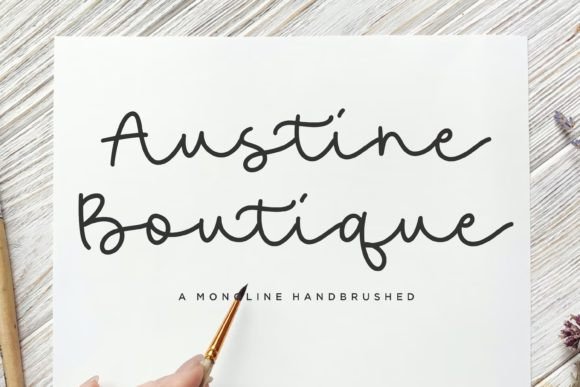
Austine Boutique
์˜ฌ๋ฐ”๋ฅธ ๋””์ž์ธ ์š”์†Œ๋ฅผ ์ฐพ๋Š” ๊ฒƒ์€ ์–ด๋ ค์šธ ์ˆ˜ ์žˆ์ง€๋งŒ Austine Boutique๋Š” ์ž‘์—…์„ ์ฆ‰์‹œ ํ–ฅ์ƒ์‹œํ‚ค๋Š” ๋›ฐ์–ด๋‚œ ์ปฌ๋ ‰์…˜์„ ์ œ๊ณตํ•ฉ๋‹ˆ๋‹ค.
์ •๋ฐ€ํ•˜๊ฒŒ ์ œ์ž‘๋œ Austine Boutique๋Š” ๊น”๋”ํ•œ ๋ฒกํ„ฐ, ๋ถ€๋“œ๋Ÿฌ์šด ํƒ€์ดํฌ๊ทธ๋ž˜ํ”ผ ๋ฐ ์•ˆ์‹ฌํ•  ์ˆ˜ ์žˆ๋Š” ์ƒ์—…์šฉ ๋ผ์ด์„ ์Šค๋ฅผ ์ œ๊ณตํ•ฉ๋‹ˆ๋‹ค.
POD(์ฃผ๋ฌธํ˜• ์ธ์‡„) ์ œํ’ˆ, ๊ฒฐํ˜ผ์‹ ์ดˆ๋Œ€์žฅ ๋˜๋Š” ์†Œ์…œ ๋ฏธ๋””์–ด ๊ทธ๋ž˜ํ”ฝ์„ ๋งŒ๋“ค ๋•Œ Austine Boutique๋Š” ์ด์ƒ์ ์ธ ์„ ํƒ์ž…๋‹ˆ๋‹ค.